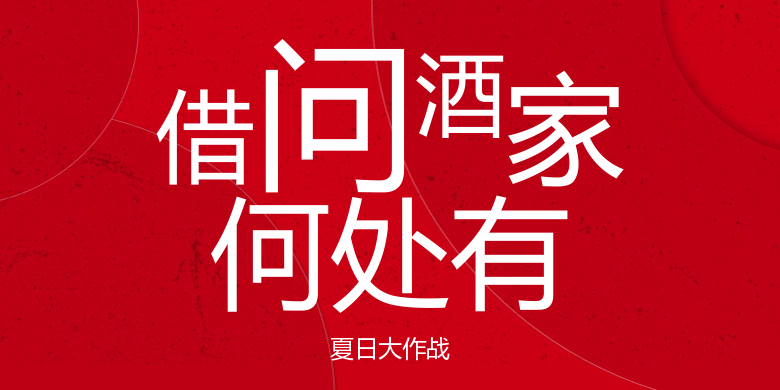
夏日大作战
夏日大作战,这款字体结构工整、笔画清晰,兼顾美观与易读性,适用于标题、正文、海报、包装、LOGO 等多种场景。字形优雅稳定,风格百搭耐看,适配日常排版与创意设计,让文字呈现更舒适、更具质感。夏日大作战一笔一画,皆是细节,以均衡的比例、流畅的线条打造舒适视觉体验,字形端正大气,风格简约现代。无论是商业设计、品牌宣传还是日常排版,都能轻松驾驭,让文字更有格调与力量。夏日大作战字体下载。